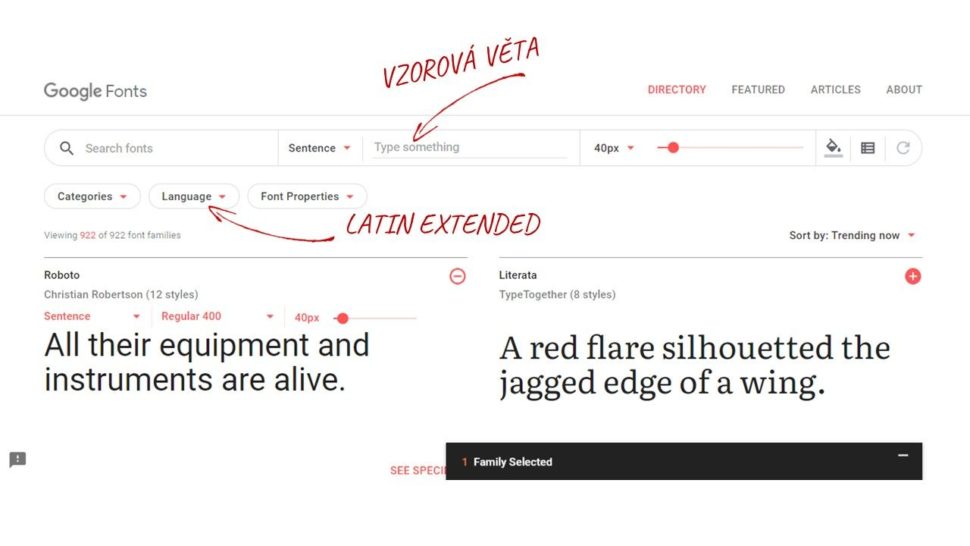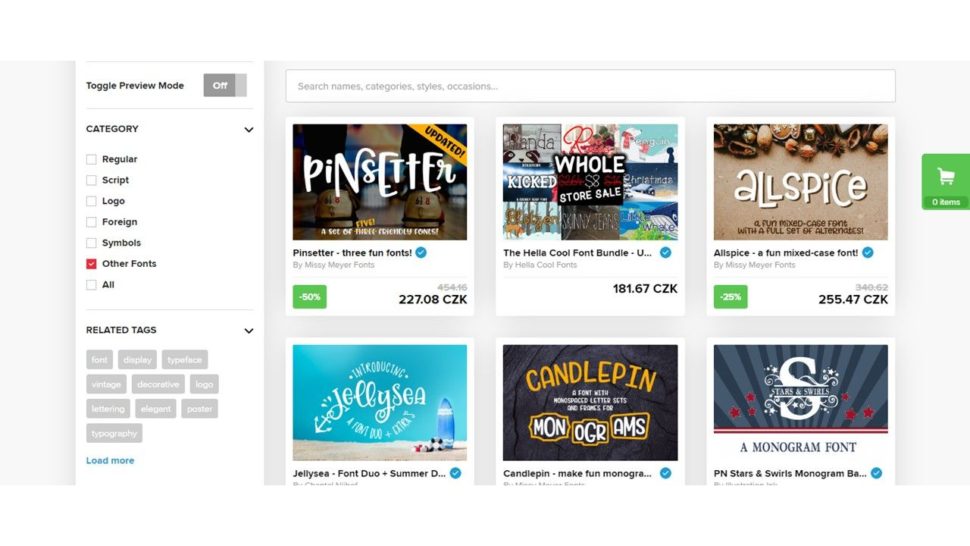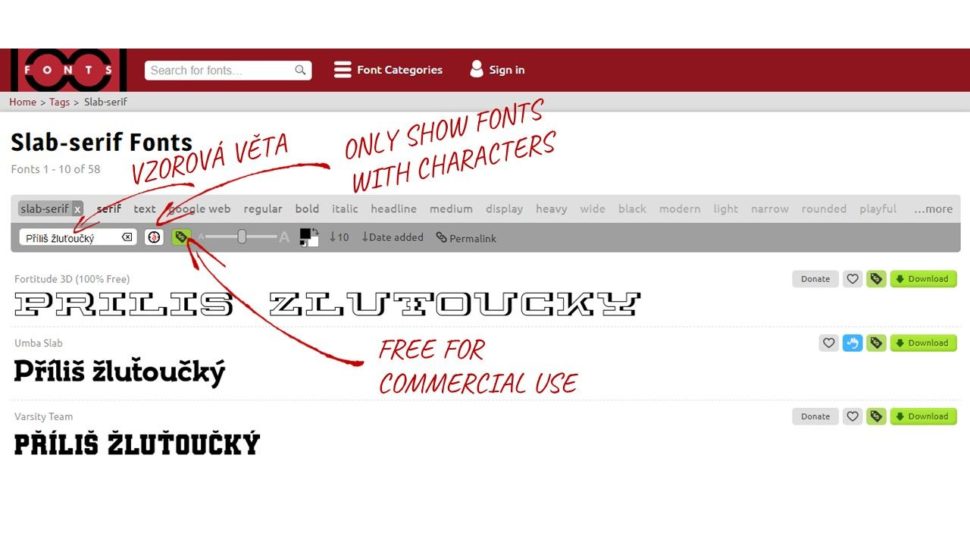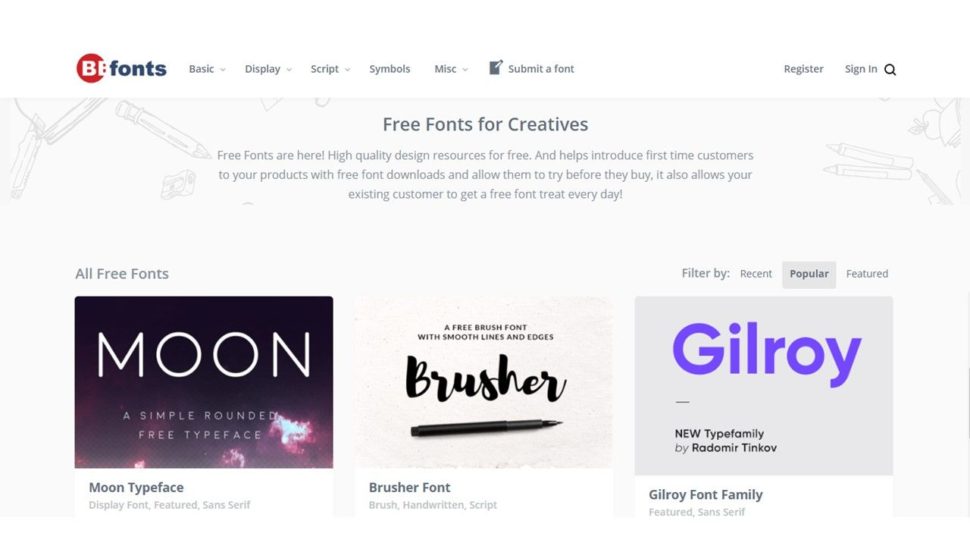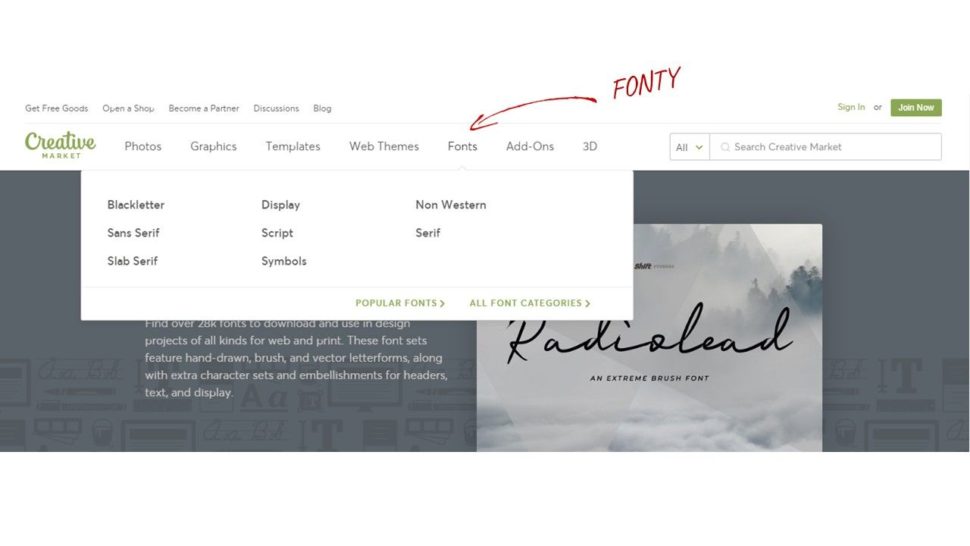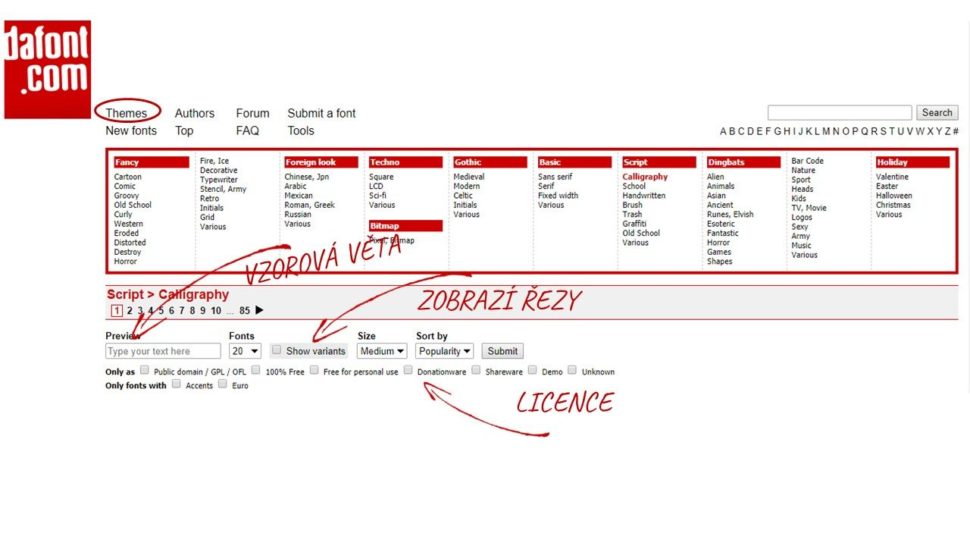
Hledáte fonty, nejlépe ke stažení zdarma? Krásná kaligrafická písma na svatební oznámení anebo minimalistické bezpatkové fonty na web?
Napíšu Vám, kde fonty hledat, ale dříve, než se vrhnete na stovky fontů v uvedených fontobankách, měli byste vědět 3 věci:
2. Důležitá je kvalita a ne kvantita. Kvalita fontů ve fontobankách je různá, zejména u fontů zdarma. Pokud vybíráte font na facebook můžete se vyřádit, ale pokud vybíráte font pro krásnou knihu, investujte u profíků.
3. Nevybírejte font „aby byl hezký“. Vybírejte takový, který vyzvedne to, co chcete říct textem. Pokud nevíte přesně jak na to, bude se vám hodit Fontotéka, kde je u každého fontu i typologie fontu a cílová skupina.
Seznam fontobank:
Včetně mých osobních poznámek a doporučení.
P.S. pokud mluvím o vzorové větě, myslím tím něco jako „Příliš žluťoučký kůň zběsile řehtal…“. Jednoduše větu, kde máte co nejvíce znaků české diakritiky.
GOOGLE FONTS
Ověřený zdroj fontů dobré kvality, 9 z 10 webdesignérů vyžaduje fonty právě z tohoto zdroje. Velkou výhodou je legální použití i pro komerční účely a jednoduchost importu na web.
Nevýhodou je potom omezený výběr, zejména u ručně psaných fontů – často pak na webech potkáváte stále dokola ty samé.
Česká diakritika: Ne všechny fonty ji mají. Doporučuji zadat do Languages Latin Extended a do pole Sentence zadat vzorovou větu.
CANVA
Skvělý nástroj, ve kterém si i amatér může vytvořit základní grafiku. Součástí je i poměrně velký výběr fontů, v placené verzi si můžete i nahrávat nové fonty. Při hledání takových, které píšou správně česky se asi pěkně zapotíte, proto jsem pro vás kdysi připravila historicky nejúspěšnější tahák na mém webu. Klidně si ho stáhněte, ať ušetříte čas.
ČESKÉ FONTY
Skvělý počin, založit fontobanku, ve které najdete pouze fonty, které mají českou diakritiku. Velkou výhodou je, že se můžete soustředit na vyhledávání podle dalších kritérií a háčky a čárky neřešíte. Nevýhoda je potom fakt, že od roku 2010 proběhla pouze jedna malá aktualizace v lednu 2016. Třeba se soubory *rar je v současnosti těžké pořízení.
Pozor, i když autoři uvádí, že všechny fonty je možné používat zdarma, čtěte pozorně licence. Někdy to platí pouze pro soukromé užití.
(Stejnou myšlenku fontobanky s českými fonty měli autoři podobného webu www.ceskefonty.com. Nápad dobrý, provedení a kvalita nabídky už pokulhává. Některé fonty nejdou stáhnout a na webu neexistuje kontakt, na který by bylo možné se obrátit.)
FONTSQUIRREL
Můj oblíbenec. Fonty jsou vesměs kvalitní, velký výběr, přehledné třídění a dokonce můžete vyhledávat i podle češtiny. Jenom se vám pak výběr zúží na desetinu, doporučuji raději vyhledávat bez jazykového filtru a kontrolovat diakritiku při zadání vzorové věty. Ta se bohužel může zadávat pouze v detailu každého fontu, to je jediná nevýhoda, kterou jsem našla.
Web je pečlivě udržovaný, stále přibývají nové fonty.
Tip č. 1: pokud zde najdete font, který se vám líbí, ale neumí česky, zkuste si ho vyhledat v Google fontech. Občas se objeví i tam ve verzi, která českou diakritiku má.
Tip č. 2: Když se vám font fakt líbí, ale free verze neobsahuje českou diakritiku, zkuste placenou verzi. Stalo se mi, že ta háčky a čárky obsahovala a navíc máte lepší pozici na vyjednávání s autorem fontu, jestli vám nepošle odkaz na verzi, která diakritiku má.
1001 FONTS
Méně přehledný web, kvalita fontů kolísá od velmi pochybné po dobrou. Výhody má dvě. Je možné zadat vzorovou větu na úvodní stránce – ihned vidíte, kde chybí česká diakritika, ale nedá se podle nich třídit.